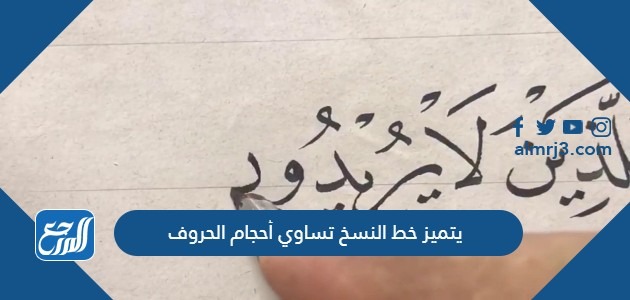
يتميز خط النسخ تساوي أحجام الحروف
يتميز خط النسخ تساوي أحجام الحروف، تتعدد أنواع الخطوط التي يتم كتابة حروف اللُغة العربية بها، ولكل نوع من الخطوط العربية سمات وخصائص مُعيّنة، كما أن حروف اللغة العربية تنقسم إلى قسمين منها ما يُكتب على السطر ومنها ما ينزل عن السطر، ومن خلال موقع المرجع سيتم التعريف بالخط العربي وأنواع الخطوط العربية والأساليب المستخدمة عند الكتابة بالخطوط العربية، كذلك خصائص الخط العربي، ومن ضمنها خط النسخ الذي يتمحور سؤالنا في هذا المقال عنه.
ما هو الخط العربي
يُعرف الخط العربي بأنّه عبارة عن فن من فنون الكتابة في مختلف اللغات التي تُستخدم الأحرف العربية الثماني وعشرون حرفًا، ويُعد من أهم ما يميز الكتابة العربية هو تشابك حروفها، حيث تكتب الحروف بشكل متصل مع بعضها البعض، مما يضيف نوعاً من المرونة والتشكيل فيها من خلال ما يسمى بالمد والاستدارة والتزوية والتشابك والتداخل والتركيب، بالإضافة إلى أنّه تم استخدام فن الخطوط في الزخرفة أي في تزيين المساجد والقصور، إذ يعتمد الخط العربي على مجموعة من القواعد الذي تُعطيه الجمال ومن اهمها التناسب بين الخط والنقطة والدائرة، كما يستخدم الخطاطون نفس العناصر التي تعتمدها الفنون التشكيلية الأخرى، مثل الخط والكتلة.
يتميز خط النسخ تساوي أحجام الحروف
يتميز خط النسخ بالعديد من الخصائص والتي يُعد أبرزها تساوي أحجام الحروف العربيّة، حيث أنه يتم المساواة ما بين على أحجام الحروف أثناء الكتابة، بالإضافة إلى أنه يتميز بأن الحروف تتخذ أشكال مختلفة عند رسمها ويوجد فيه إمّا نقطتين أو ثلاث نقاط، وبذلك فإن الإجابة على السؤال السابق هي:
- العبارة صحيحة.
ما هي الأساليب المستخدمة في كتابة الخط العربي
هناك العديد من أشكال الخطوط العربية التي تم استخدامها بأشكال متعددة، ولكن يتم تصنيف جميع الخطوط العربية ما بين نوعين وهما الأسلوب الجاف والأسلوب اللين.
الأسلوب الجاف
ويسمى أيضا بالأسلوب القاسي أو المزوي، وتتميز طريقة كتابة حروفه بالرزانة والوقار، كما يتم استخدام الأدوات الهندسية لرسم الزوايا القائمة، بالإضافة إلى أنه تم استخدام خطوطه في كتابة المصاحف الأولى، وهناك العديد من الخطوط التي تندرج تحت هذا الأسلوب ومن أهمها:
- الخط الكوفي الهندسي.
- الخط الكوفي المزخرف.
- الخط المضفور.
- الخط المورق.
- الخط المشجر.
- الخط المزهر.
- الخط الكوفي الأيوبي.
الأسلوب اللين
من مميزات هذا الأسلوب بكتابة الأحرف برشاقة وانسيابية، كما يستخدم الخطاطون قلم الخط أو القصبة، في هذا الأسلوب ومن أشهر أنواع الخطوط الذي يتضمنه هذا الأسلوب هي:
- خط الثلث.
- خط النسخ.
- التعليق.
- الديواني
- الرقعة.
- الإجازة.
- خط الطغراء.
- المحقق.
- الريحان.
- خط النسخ.
خط النسخ
هو نوع من أنواع الخطوط، يستخدم بشكل كبير في الكتابة، وذلك بسبب فوائده العديد. ويستخدم بشكل كبير في كتابة وطباعة مجموعة كبيرة من النصوص الجامعية والعلمية، وأيضًا يُستخدم في كتابة الروايات، كما إنه مناسب جداً للأشخاص من جميع الأعمار والمراحل.
مميزات خط النسخ
لخط النسخ العديد من الخصائص والمميزات، والتي نُوردها فيما يلي:
- سهل في الكتابة حيث يمتاز بسرعة الكتابة فيه.
- يعمل على توضيح كتابة الحرف وإظهار جماله
- يستخدم هذا الخط في كتابة القرآن الكريم.
- أصبح هو الخط الافتراضي في الحواسيب .
- أناقة تصميمه وجلال شخصياته ووضوح لغته.
- جميع أحرف الخط تمتلك نفس الحجم مما يميزها عن غيرها.
- سهل في قراءته وكتابته.
- متوافق مع جميع معايير اللغة العربية.
- يجمع بين البساطة والرزانة من حيث سهولة الكتابة.
- بسيط في الإتقان.